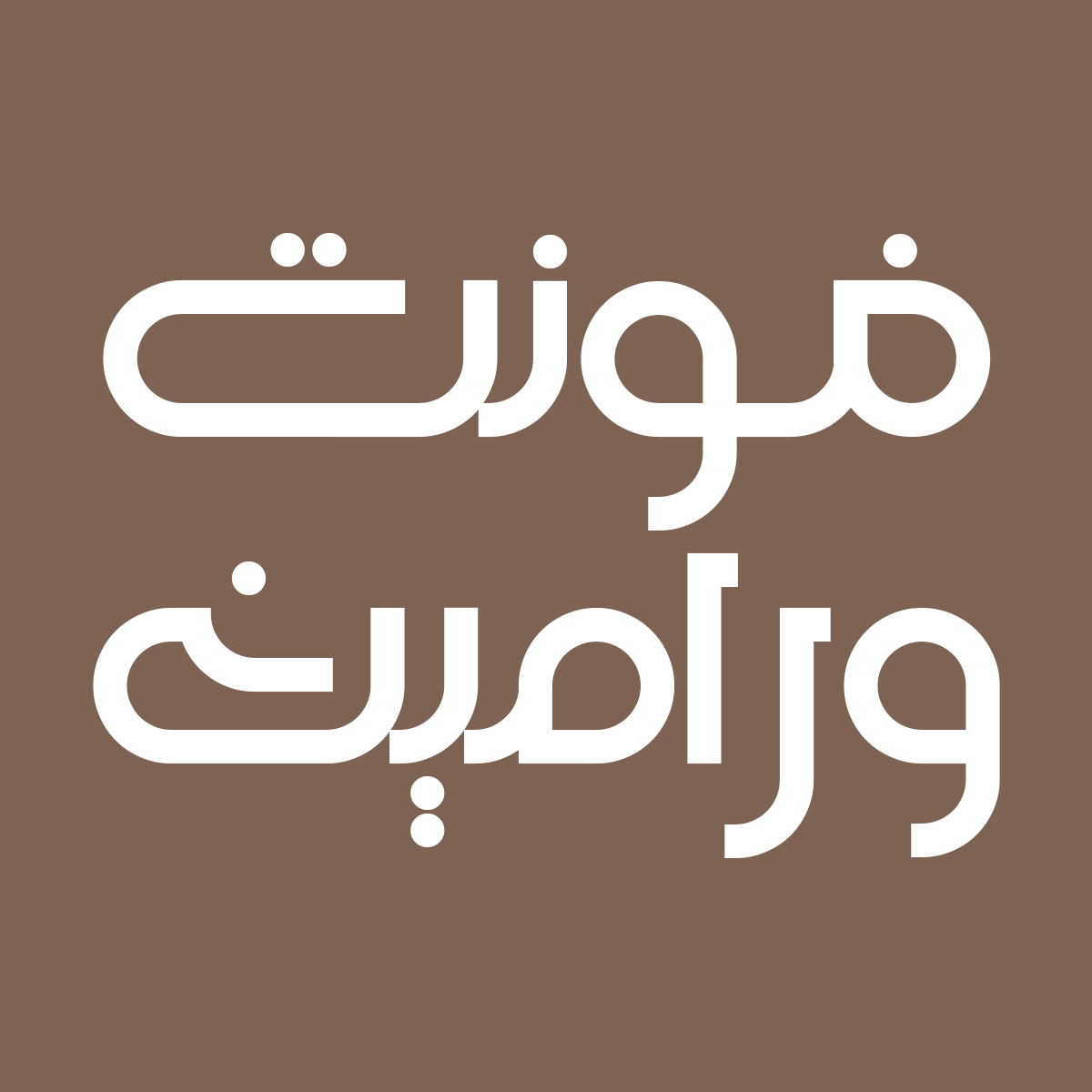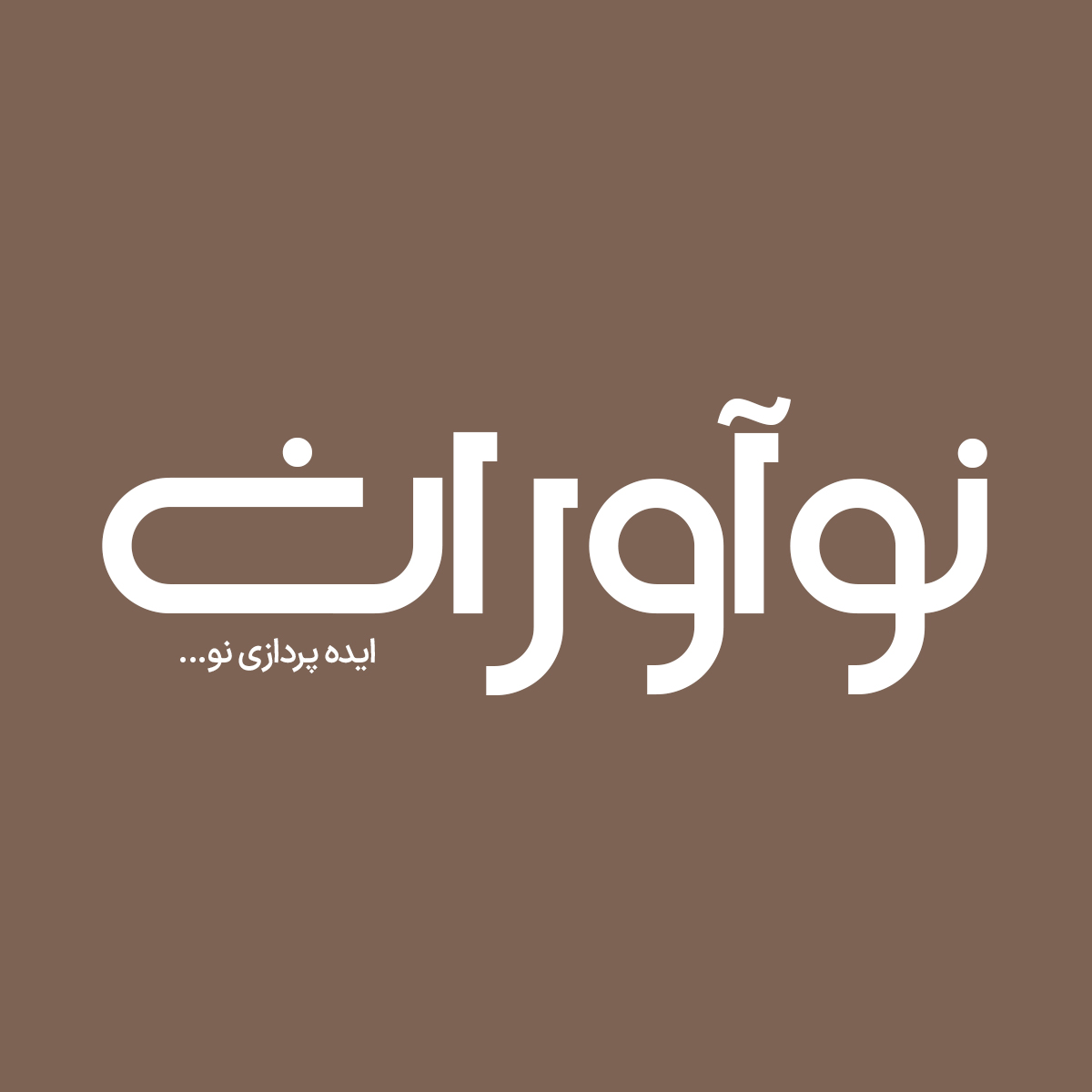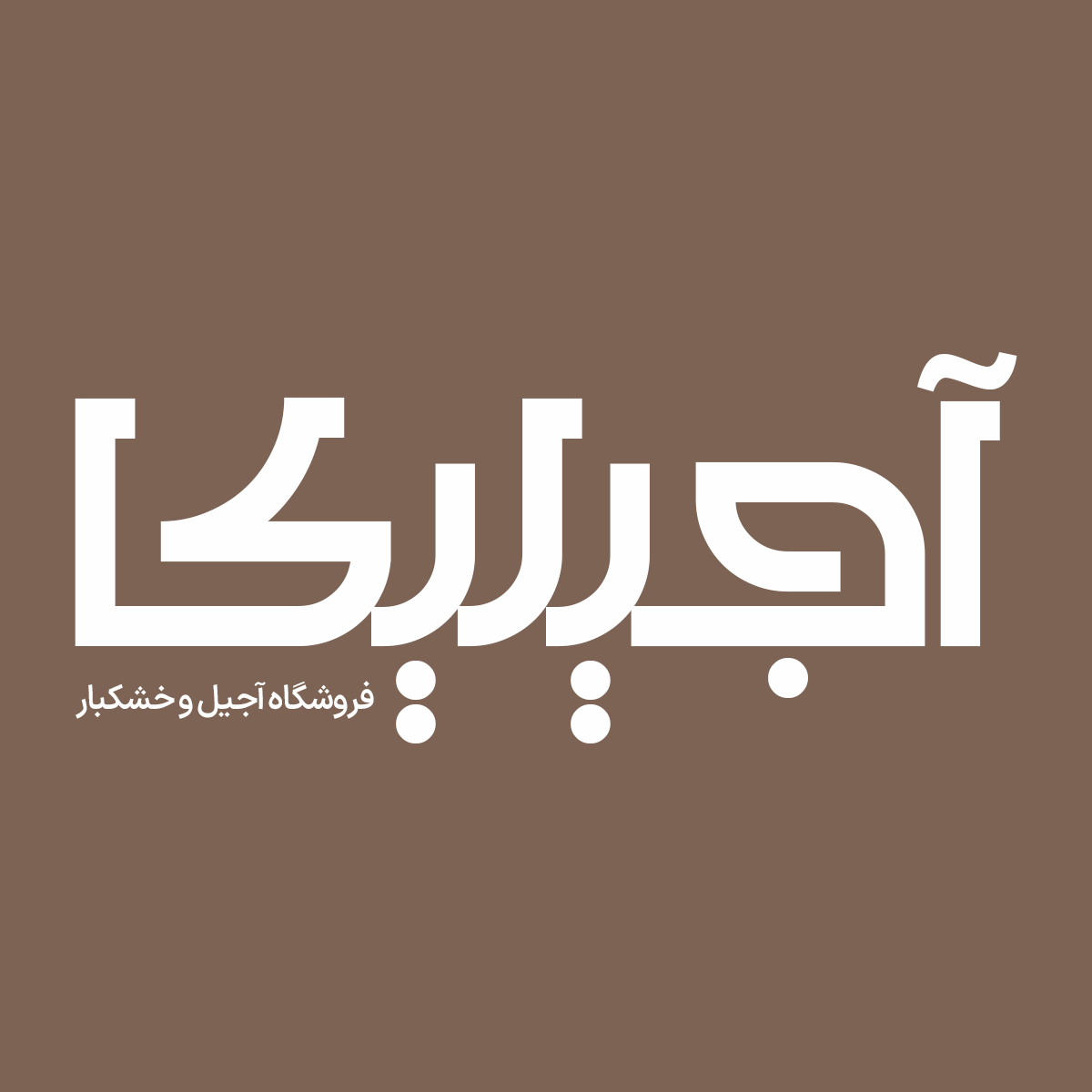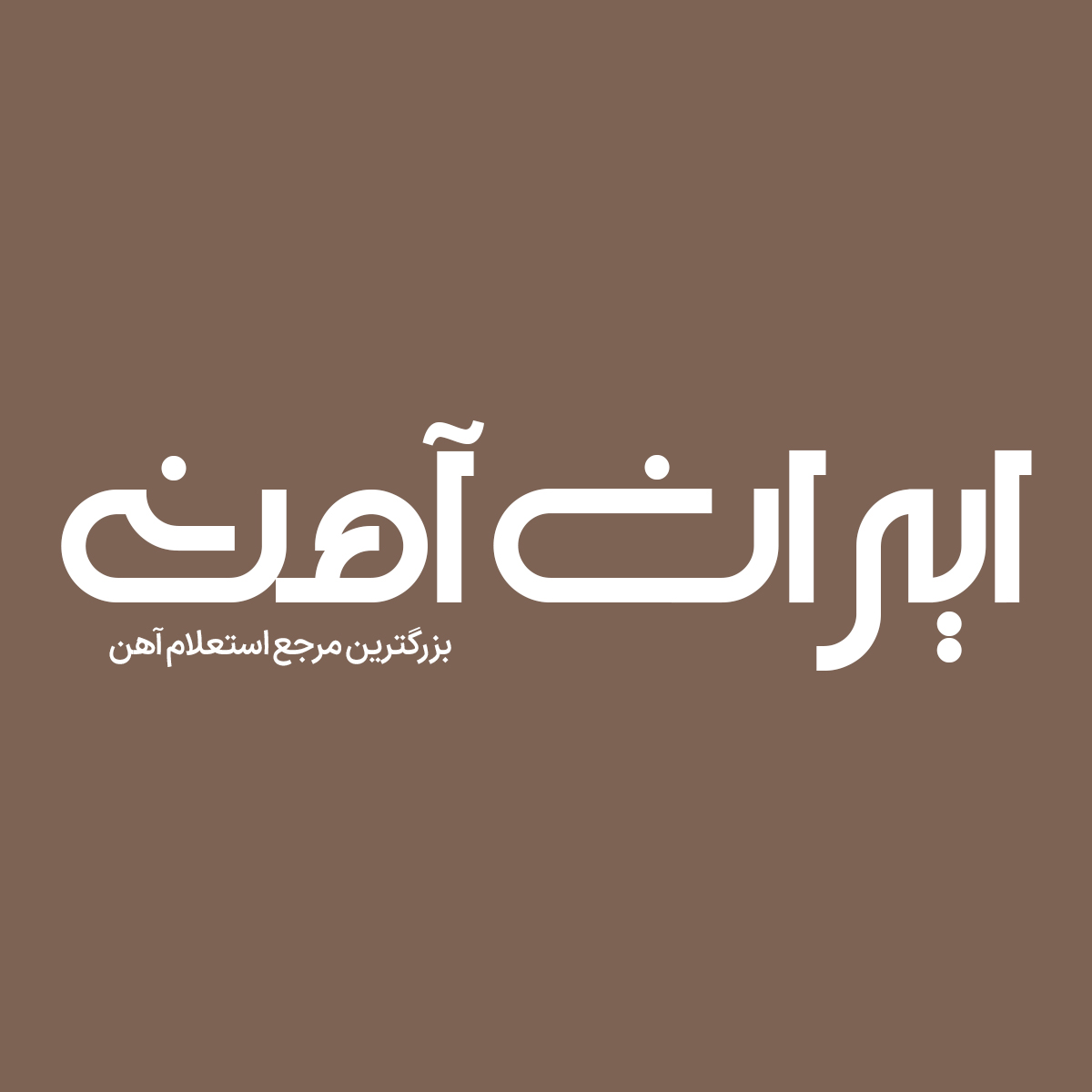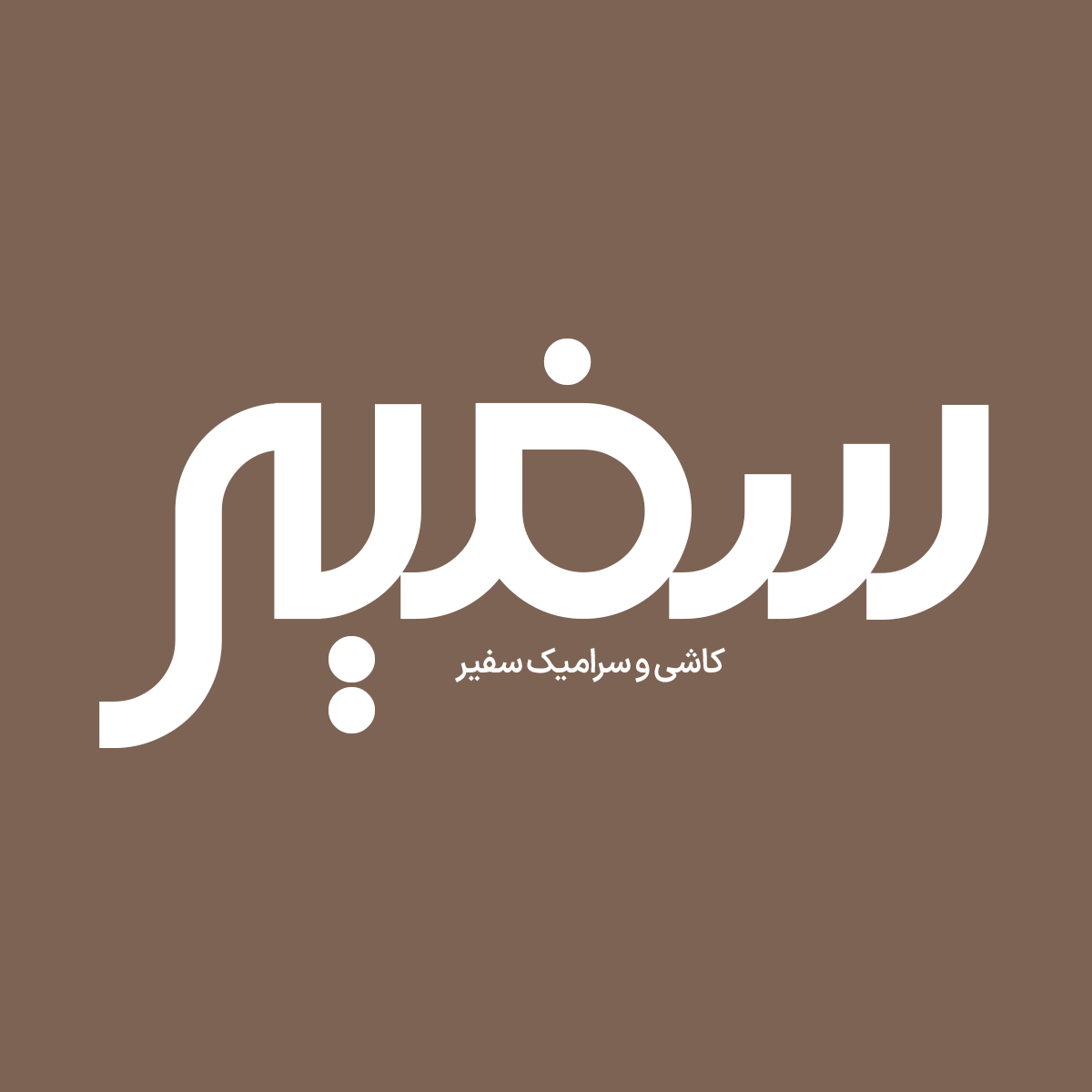
فونت فارسی ورامین Varamin Font
فونت فارسی ورامین از دسته فونت‌های مدرن است. از این فونت می‌توان برای طراحی لوگو، طراحی اسم، دیوار نوشته‌های هنری، طراحی بنر، طراحی پوستر و غیره…
فونت فارسی ورامین از دسته فونت‌های مدرن است. از این فونت می‌توان برای طراحی لوگو، طراحی اسم، دیوار نوشته‌های هنری، طراحی بنر، طراحی پوستر و غیره استفاده کرد و این به جهت شکستگی‌ها و انحناهای متعادل، همنشینی روان حروف در کنار هم، حجم دهی بالا و اتصالات مختلف است. در ادامه برای شما نمونه تایپ‌های این محصول حرفه‌ای رو آماده کردیم که می‌توانید مشاهده کنید.
• مناسب طراحی بسته بندی ها و چاپ
• فونت ویژه تبلیغات محیطی
• فونت طراحی کاور اینستاگرام
• فونت حرفه ای برای تولید محتوا
• فونت فارسی طراحی وبسایت
• فونت طراحی لوگو تایپ فارسی
• مناسب استفاده در تابلو های چلنیوم و طراحی حروف
پیشنمایش و نمونه تایپ های فونت ورامین